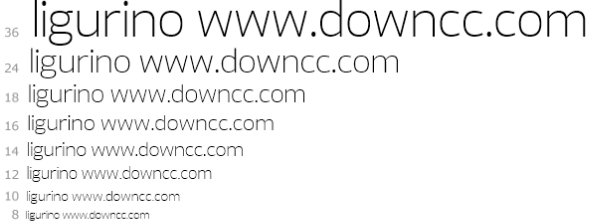
ligurino字體是一款無襯線字體,字跡綿長而娟秀,支持英文輸入,中文字體無法顯示,但整體造型上十分典雅別致,讓英文內(nèi)容不一樣的展示,綠色資源網(wǎng)誠意推薦!
ligurino是一種無襯線字體,纖細,修剪和低調(diào)。受到80年代的雛菊輪打印機的啟發(fā),這種字體沒有任何裝飾,使得很多其他字體難以閱讀,特別是在小尺寸的情況下,平衡的線條和慷慨的設(shè)計美感。
無襯線字體專指西文中沒有襯線的字體,與漢字字體中的黑體相對應(yīng)。與襯線字體相反,該類字體通常是機械的和統(tǒng)一線條的,它們往往擁有相同的曲率,筆直的線條,銳利的轉(zhuǎn)角。